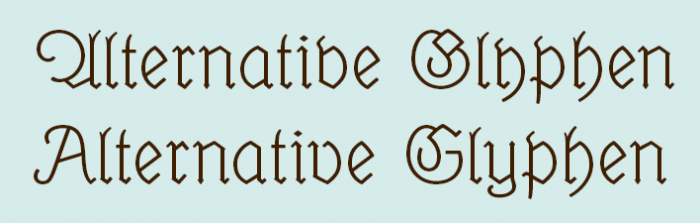
Fraktur mit modernen Glyphen-Varianten?
Kennt jemand neben der Unifraktur Maguntia weitere Frakturschriften, die einem die Wahl zwischen klassischen Formen und an heutige Antiqua-Lesegewohnheiten angepasste Formen lassen oder letztere als alleinige Variante benutzen?
(Nicht gemeint sind gotische Schriften, wo der Unterschied ohnehin geringer ausfällt, oder Antiqua-Schriften mit gebrochenem Duktus.)
Nun, ich habe dies in meiner Version der Fetten UNZ1 Fraktur gemacht,  zwar nicht in einem Font, weil ich an die vielen nicht Opentype-Funktions-Nutzer denke, sondern in 2 getrennten Versionen, eine mit dem "langen" k, dem r ähnlichen r und der entsprechenden ck-Ligatur, und eine Modern-Version mit an den Antiqua-Stil angepasstem k und r.
Sie sollte ja weiterhin als die bekanntge Fette Fraktur erkennbar sein, nur eben ohne die Einschränkungen der meisten digitalen Fassungen, die oft weder langes s noch Ligaturen enthalten. Aber vielleicht schjau ich mir das noch mal  genauer an, und entwickel das weiter zur "modernen fetten Fraktur", oder "fette 21st Century Fraktur"?
Möglicherweise liege ich falsch, aber würde die Algo FY nicht in diese Kategorie passen? Ich bin gerade beim FontShop drüber gestolpert … Wenn nicht, kannst Du diesen Post gerne wieder löschen.  :-)
Aber ist die Algo nicht an sich auch eben eine »Antiqua mit gebrochenem Duktus«?
Oder zumindest einfach eine gebrochene Schrift, aber keine Fraktur?
Ist so etwas gedacht?
Ja, genau. Wobei du mir jetzt als Lösung für meine Frage meine eigenen Lösungen vorlegst. Ich hatte beim Zeichnen dieser Alternativzeichen der modernisierten Elfen-Fraktur diesen Strang hier eröffnet.   ;-)
Aber es passt natürlich trotzdem und kann ja für weitere Diskussionen zu dieser Frage nützlich sein.
Ha! So schließt sich der Kreis.
Ich habe zwar beide Fonts gekauft, werde Typ B aber wahrscheinlich nie für Drucksachen nutzen.